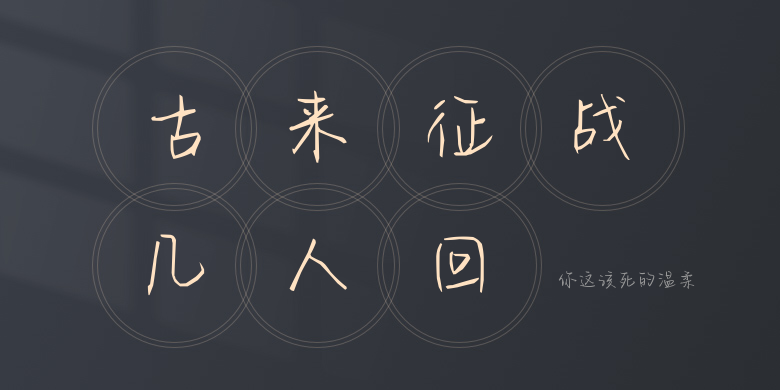
你这该死的温柔
你这该死的温柔,这款字体结构工整、笔画清晰,兼顾美观与易读性,适用于标题、正文、海报、包装、LOGO 等多种场景。字形优雅稳定,风格百搭耐看,适配日常排版与创意设计,让文字呈现更舒适、更具质感。你这该死的温柔一笔一画,皆是细节,以均衡的比例、流畅的线条打造舒适视觉体验,字形端正大气,风格简约现代。无论是商业设计、品牌宣传还是日常排版,都能轻松驾驭,让文字更有格调与力量。你这该死的温柔字体下载。